视觉艺术字体是字体设计的一个重要分支,它们具有高度的艺术性和创意性,常用于艺术作品和广告设计中。下面介绍一些独特的视觉艺术字体。
1、水墨字体:
水墨字体具有中国传统文化的特色,其笔画宽细、粗犷、流畅,呈现出浓郁的文化气息。水墨字体适用于海报设计、文化节庆等场合。
以印品潮牌体为例。这是一款大气灵动的中国风毛笔字体,笔画饱满浑厚、又不失刚劲,牵丝连带的笔画显得字体浪漫洒脱,不仅有端庄大气,而且还有一种灵动的姿态。
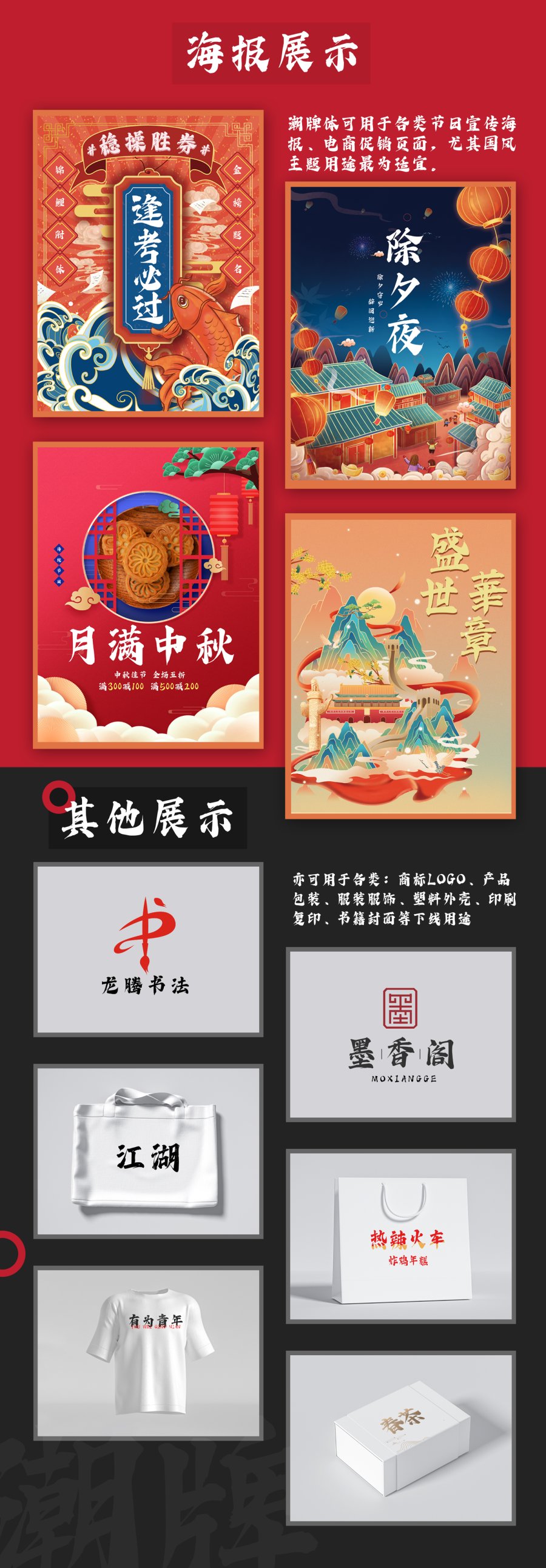
2、几何字体:
几何字体的设计风格偏向于现代感和简洁感,其构成基于几何图形的基本元素,表现出一种冷静、科技感的艺术风格。几何字体适用于科技产品、创意广告等场合。
逐浪喜迎国庆方盾体字体设计风格主要以简约、时尚为主,长方形,正方形设计,类似中国古代的方盾、库布(古钱币名),力求达到形式端正,字体设计没有过多的累赘笔画,尽量采用抽象方式达到笔画简单、清爽为楷的效果。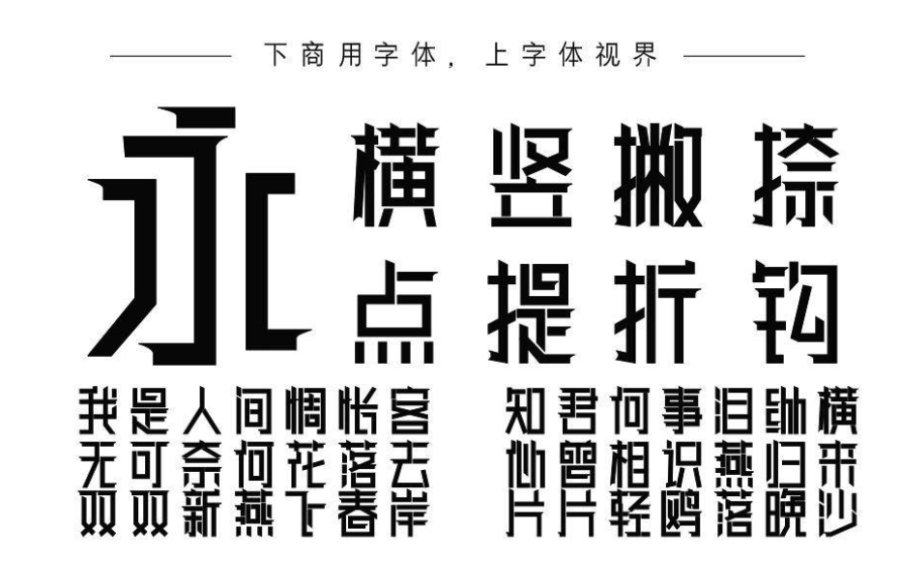
3、手写字体:
手写字体的设计以仿真手写字为主,其特点是有一定的凌乱感,个性十足。手写字体适用于卡通、广告、文化创意产品等场合。
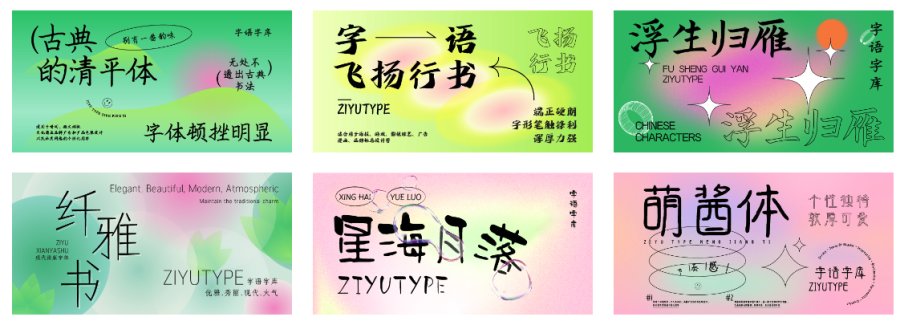
视觉艺术字体是字体设计的重要分支,它们具有独特的创意和表现手法,能够让作品更加丰富多彩。希望以上介绍的几种视觉艺术字体能够为你的设计工作提供灵感和帮助。